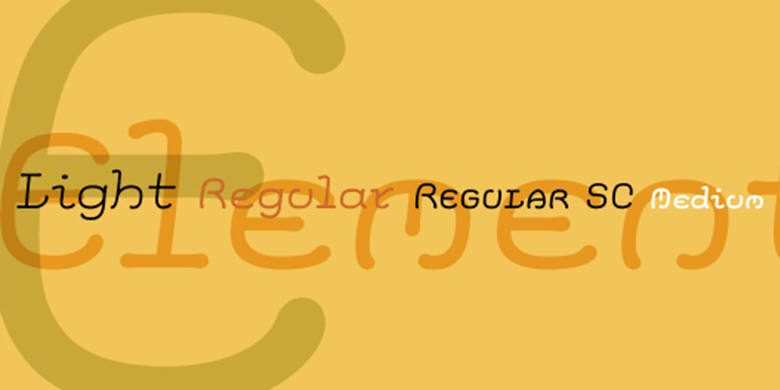
德国设计师Hans-Jurgen Ellenberger最初在1975年开发了Elementis的概念。为了创作一个更圆、更自然的打字机手写体,Elementis的设计诞生了。与打字机的根源一样,Linotype的Elementis比人们对这一类型的作品的期待更有个性。这些信件显示出一种令人愉快的古怪性质,这肯定会点亮任何文件。Elementis可以用于多种字号: 虽然字母在大的显示设置中效果最好,但也可以创建大小为12点或更小的短文本段落。
Elementis家族包含5种不同的字体: Light、 Regular、Medium、Bold 和小型大写字母。这个家族在各种竞赛中获得了许多奖项: Elementis在Linotype GmbH主办的2003年国际字体设计竞赛中获得了荣誉奖。此外,Ellenberger在2005年获得了Type Directors Club颁发的字体设计优秀证书;在一年一度的TDC2字体设计比赛中,Elementis被选为评委。
German designer Hans-Jürgen Ellenberger originally developed the concept behind Elementis in 1975. Wanting to create an alternative typewriter script that was more round and natural, Elementis’ design was born. True to its typewriter roots, Linotype’s Elementis exhibits more character than one expects from that genre. The letters display a delightfully quirky nature, which is sure to lighten up any document. Elementis may be used in a number of point sizes: although the letters function best in large display settings, short passages of text in sizes of 12 point or less may also be created.
The Elementis family contains five different typefaces: Elementis Light, Elementis Regular, Elementis Medium, Elementis Bold, and Elementis Small Caps. This family has received a number of awards in various contests: Elementis was awarded an Honorable Mention in the 2003 International Type Design Contest, sponsored by Linotype GmbH. Additionally, Ellenberger received a Certificate of Typographic Excellence from the Type Directors Club in 2005; during their annual TDC2 type design competition, Elementis was selected as a judge’s choice.""